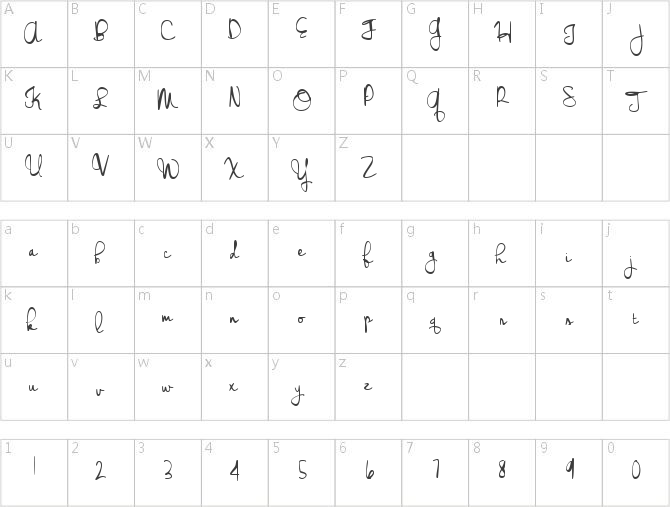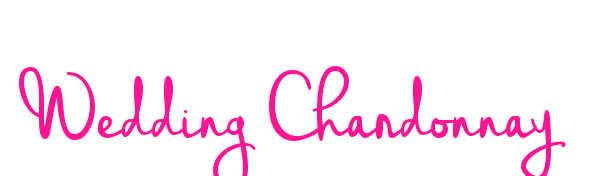
Wedding Chardonnay 详情页
Wedding Chardonnay
Wedding Chardonnay介绍
Wedding Chardonnay字体字库是一款让人赏心悦目、百看不厌的英文字体,适合各类广告和产品包装设计应用,字体大小0.1MB,格式为ttf字体,上传用户是Bot,作者/版权方为未知